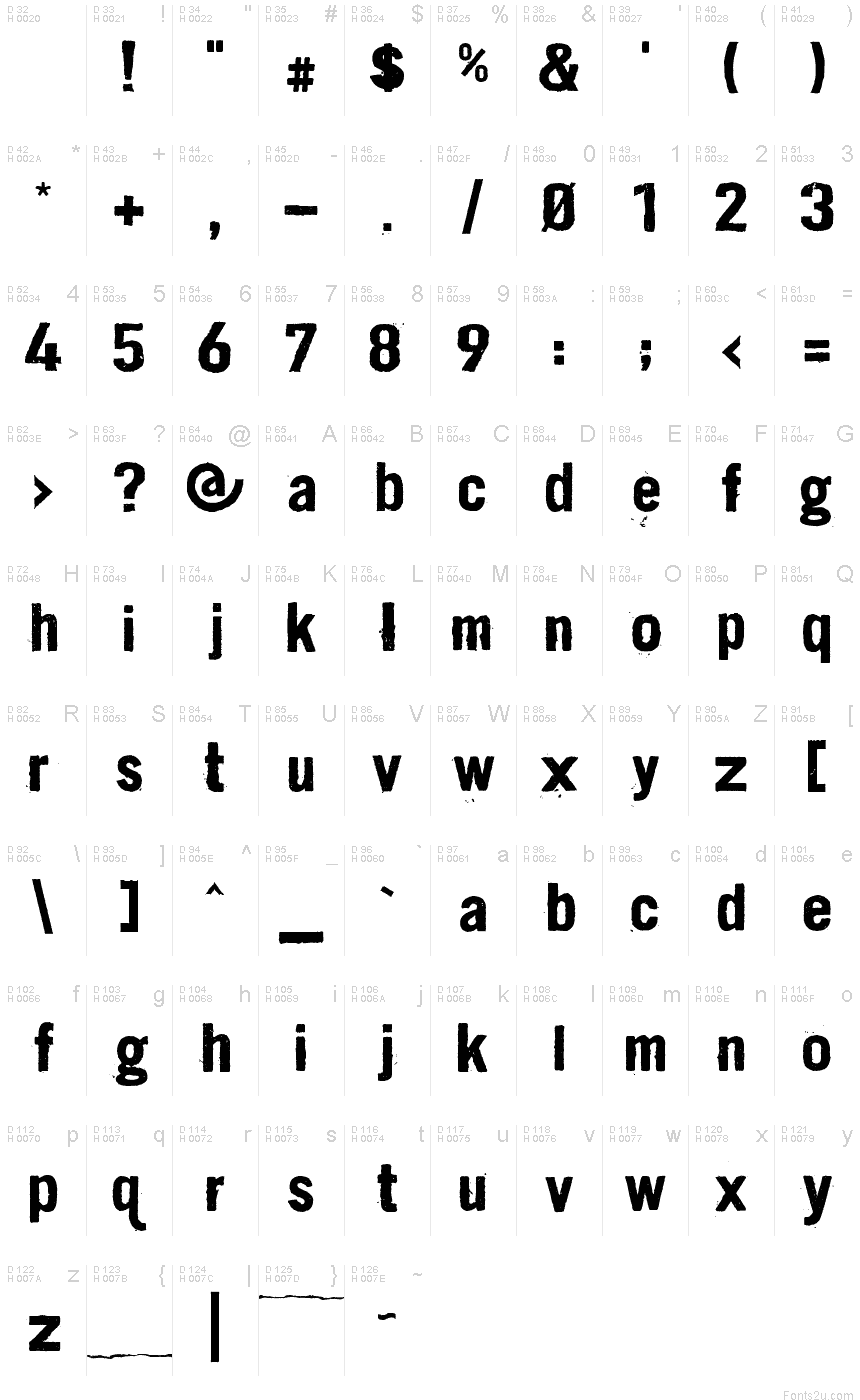
Dirt2 Stickler
Dirt2 Stickler, darmowy krój typu display o postarzanym wyglądzie od Dirt2.com, wnosi surową, atramentową energię do masywnych liter. Nierówne krawędzie, wyszarpane luki i surowe kształty tworzą efekt zużytego druku lub ręcznie wycinanych szyldów, nie tracąc przy tym wyrazistej sylwetki liter.
Ten darmowy krój świetnie pasuje do plakatów koncertowych, grafik skejtowych, okładek płyt, marek streetwearowych i kserowanych zinów. Sprawdza się również w krótkich tytułach, gdzie gęste formy i poszarpana tekstura mogą samodzielnie udźwignąć całą kompozycję.